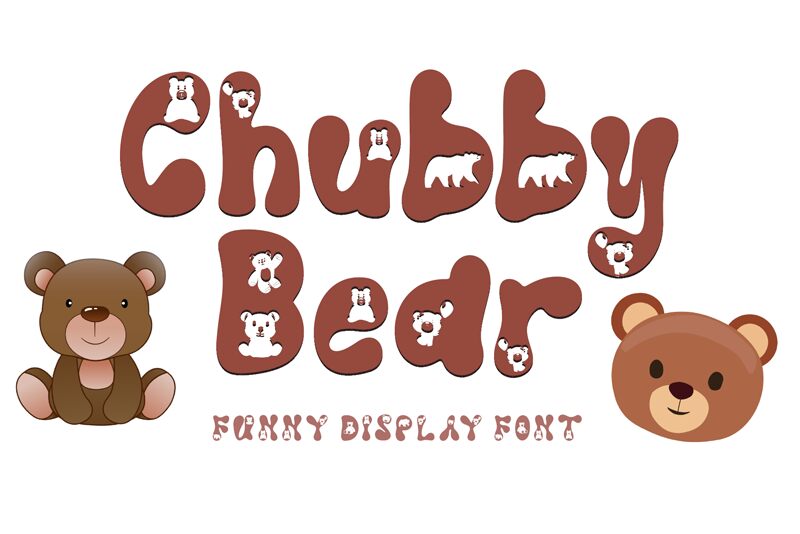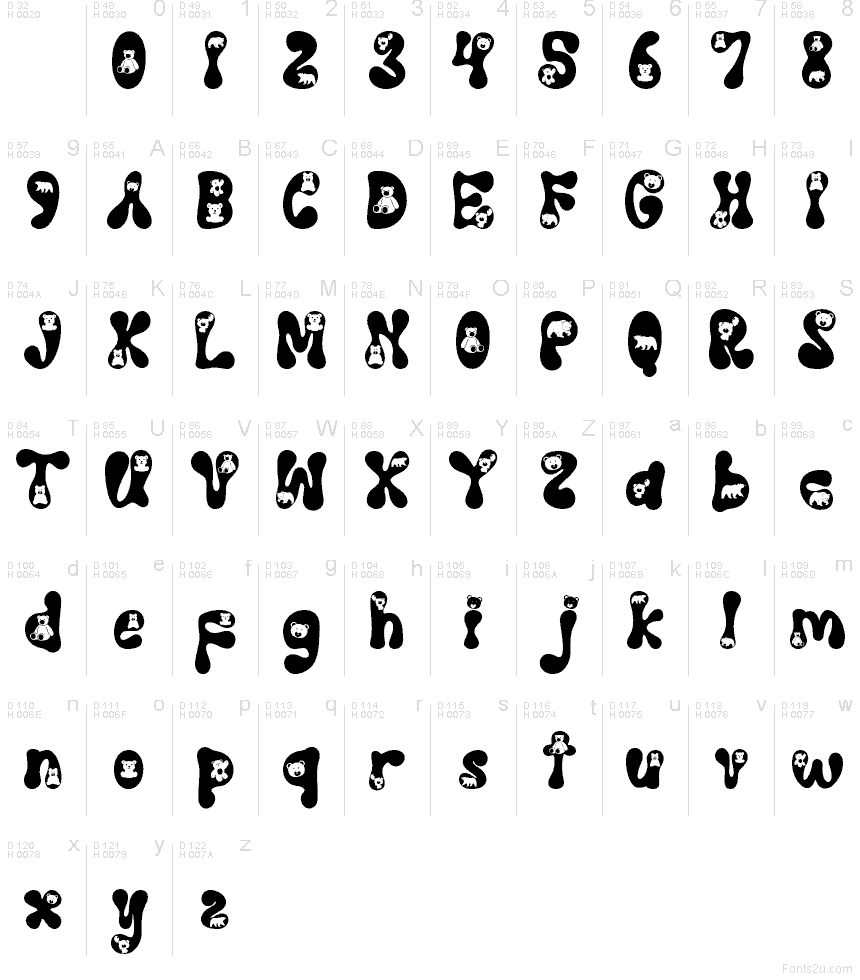
Chubby Bear
Chubby Bear de Yoga Letter es una fuente decorativa gratuita de tipo display, con letras redondeadas inspiradas en formas animales y pequeñas siluetas de osos integradas en el diseño. Sus curvas amplias y cortes suaves le dan un toque artesanal, mientras que los detalles de los ositos mantienen la unidad temática del diseño.
Chubby Bear funciona de maravilla en envases infantiles, logotipos de tiendas de mascotas, invitaciones a fiestas, etiquetas de juguetes, acentos en pósteres y gráficos divertidos para redes sociales. Esta fuente gratuita aporta un motivo temático a cualquier composición que necesite un aire amigable sin tener que recurrir a iconos externos.